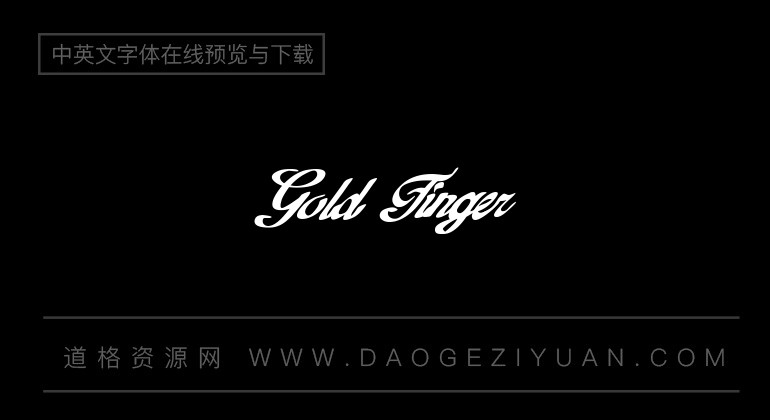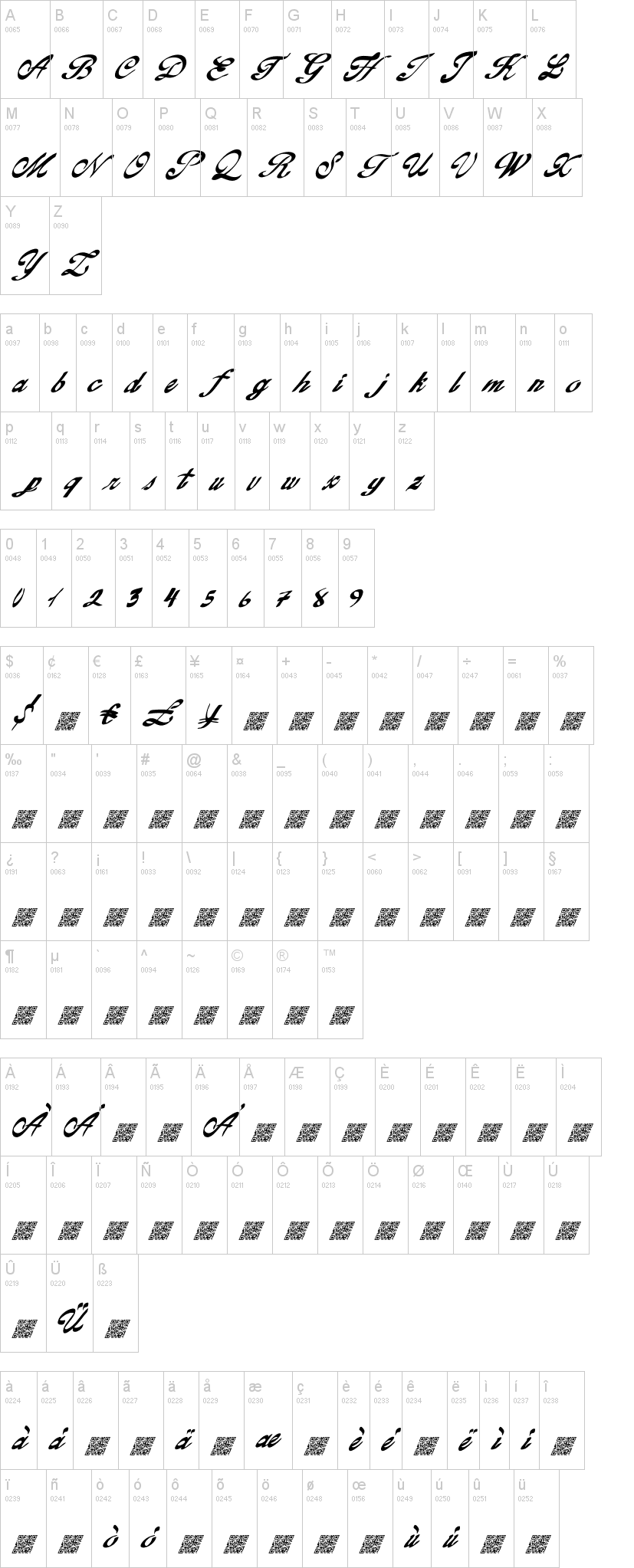
Gold Finger 字体是一款古典的美国拼花字体,由美国著名的拼花字体设计师John P. Friel于1938年设计。它具有浓郁的美国风格,拥有清晰的线条,让字体看起来更加有质感。Gold Finger字体的特点是,它的字体粗细比例恰到好处,拥有优秀的可读性,而且它的设计风格极具视觉冲击力,适合用于各种海报、标志等视觉设计中。内容介绍
Gold Finger是一款非常不错的手写艺术字体,具有很好的视觉感,适合于文化类的宣传设计、商业类品牌的广告和产品包装设计以及个性化文字排版等较多场景。